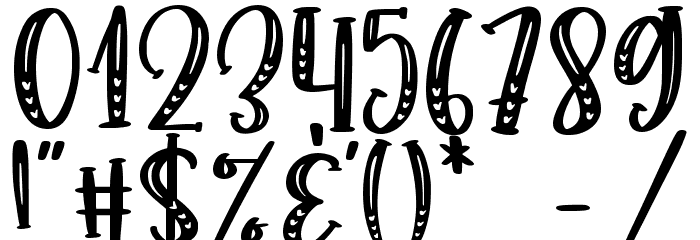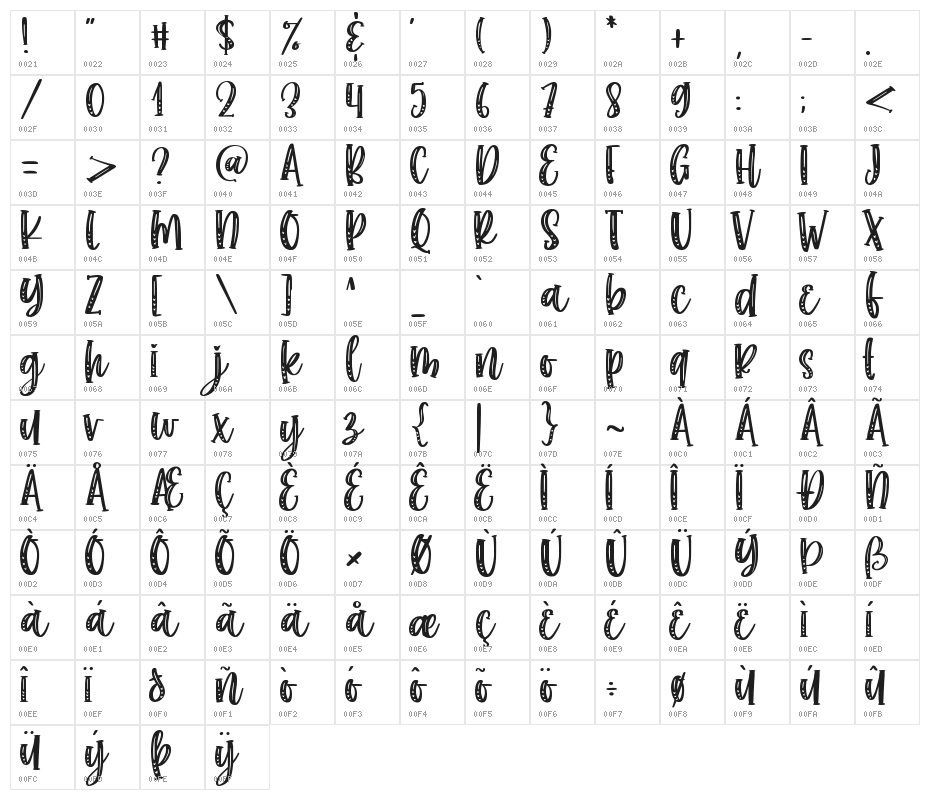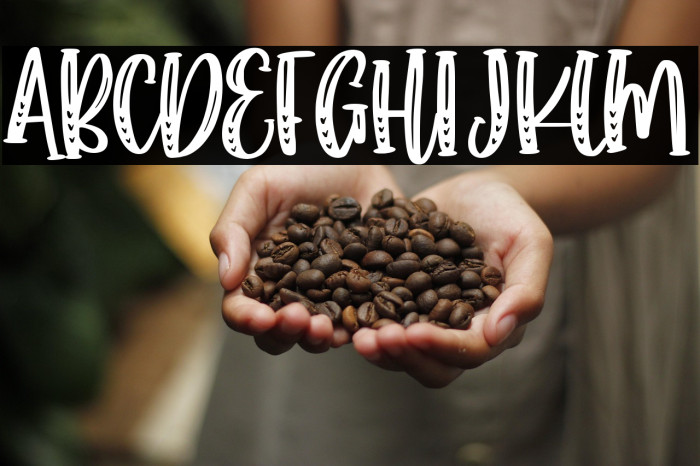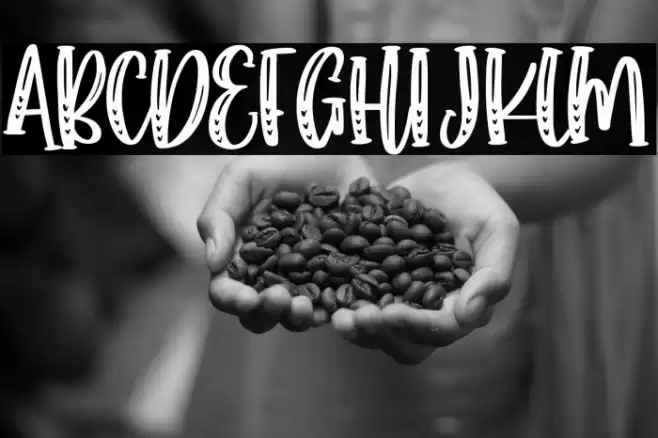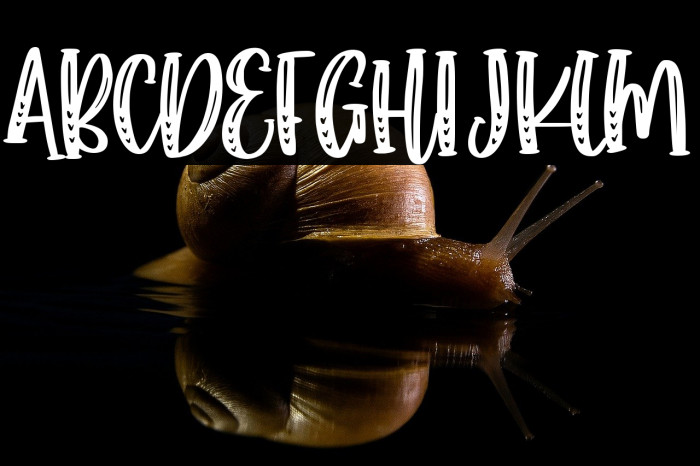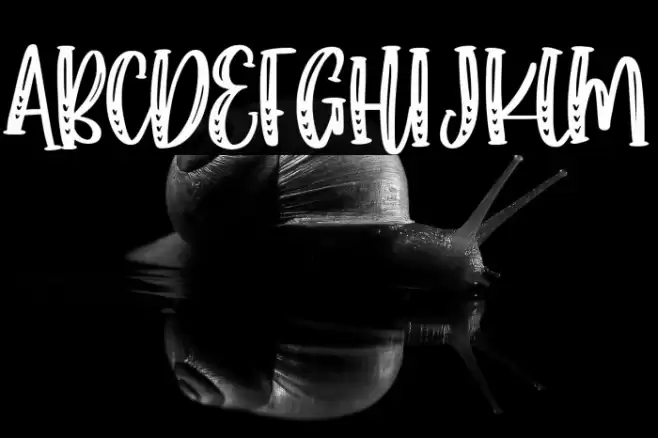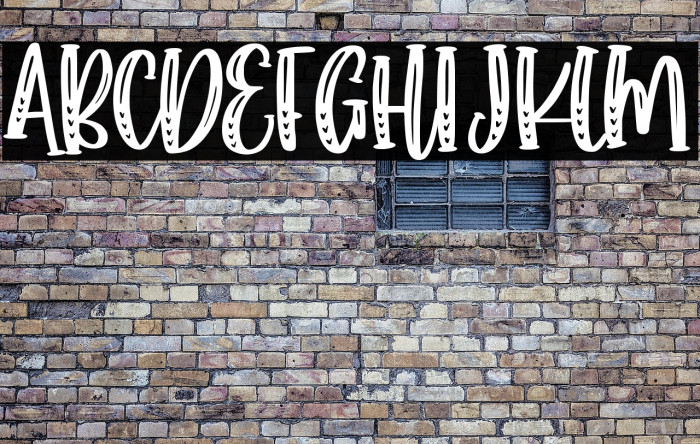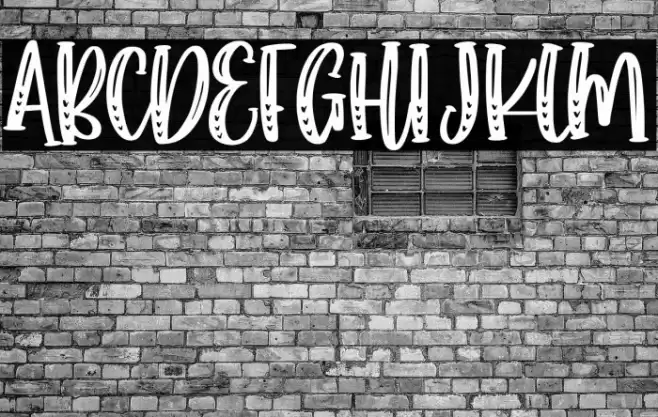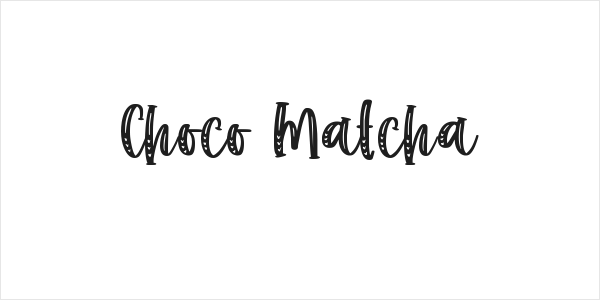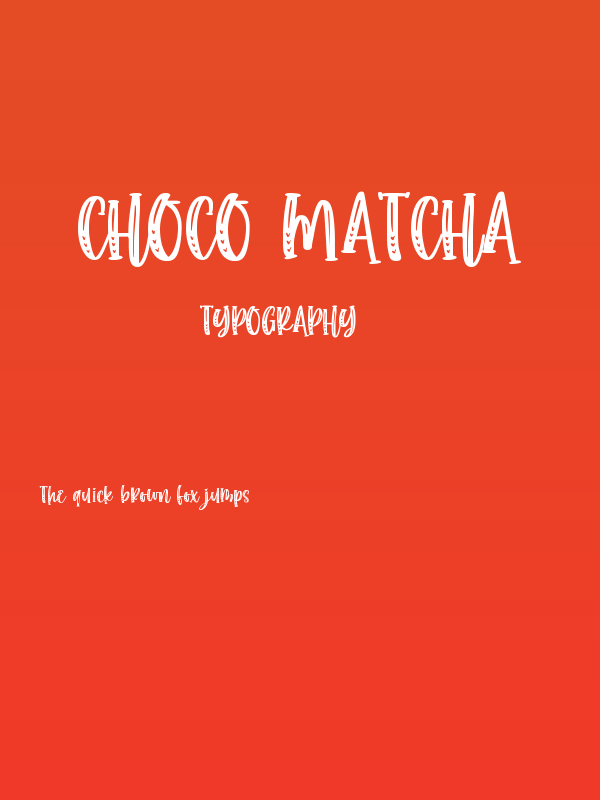
Choco Matcha Font
| Style général | Playful, Whimsical |
| Projets proposés | Ideal for children's book covers, playful branding, greeting cards, and creative posters. |